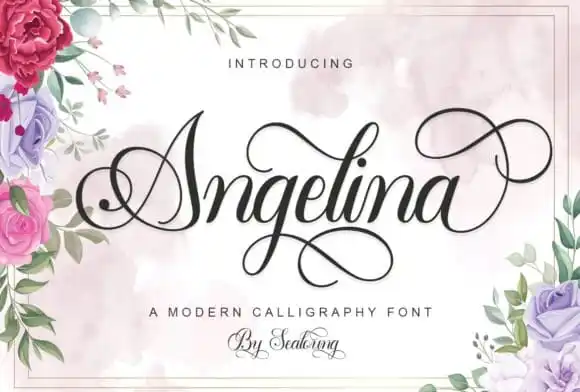
A Angelina Calligraphy Font é uma elegante fonte de caligrafia moderna criada pelo designer Sealoung para quem busca um toque distintivo em seus projetos pessoais e profissionais. Esta fonte perfeita para marca de empresa, convites e cartões de aniversário, bem como rótulos de produto, é uma escolha perfeita para quem quer um ar charmoso e sofisticado em seus designs. Com seu design moderno e toque inconfundível, a Angelina Calligraphy Font não apenas adiciona um toque pessoal aos projetos digitais ou impressos, mas também oferece flexibilidade. Suas linhas finas e detalhes precisos permitem que você personalize suas criações sem perder o aspecto distintivo da fonte. Se procura por uma fonte de caligrafia moderna e elegante para complementar seus trabalhos gráficos, então a Angelina Calligraphy Font é um excelente investimento. Seja para criar cartões de aniversário criativos ou rótulos de embalagens personalizados, esta fonte será um acréscimo valoroso aos seus projetos digitais e impressos.